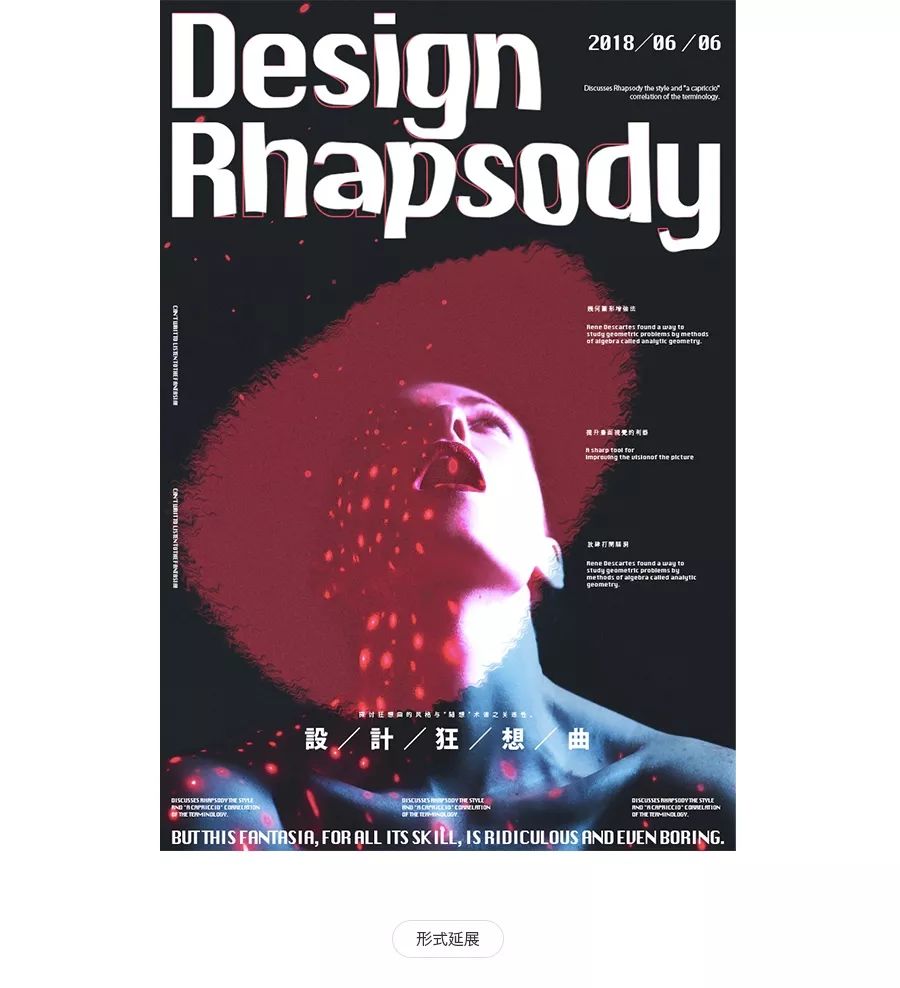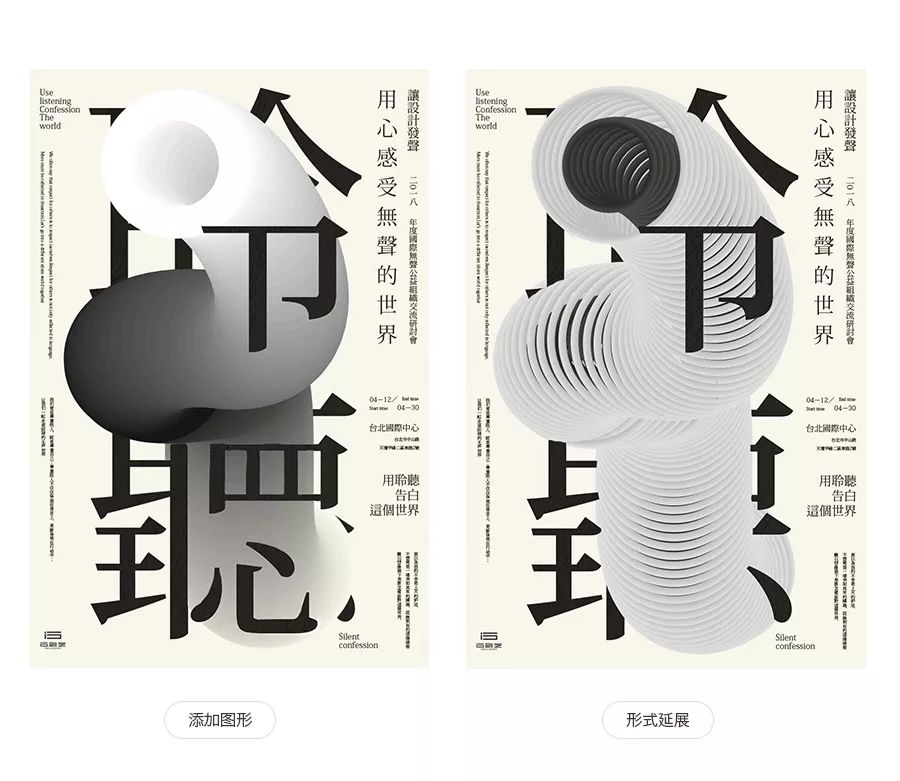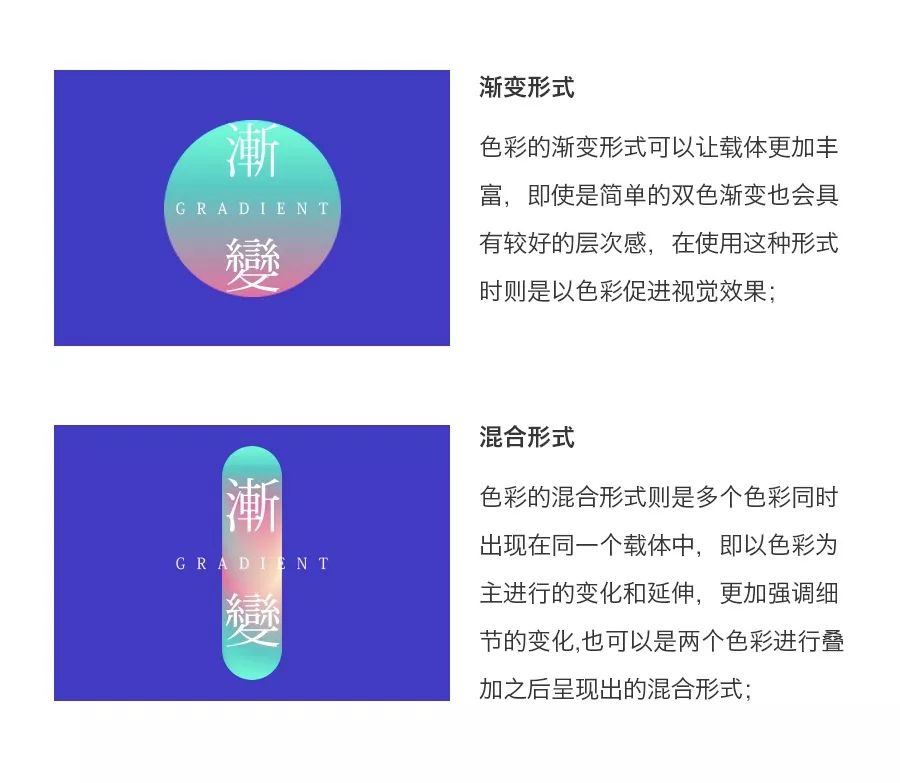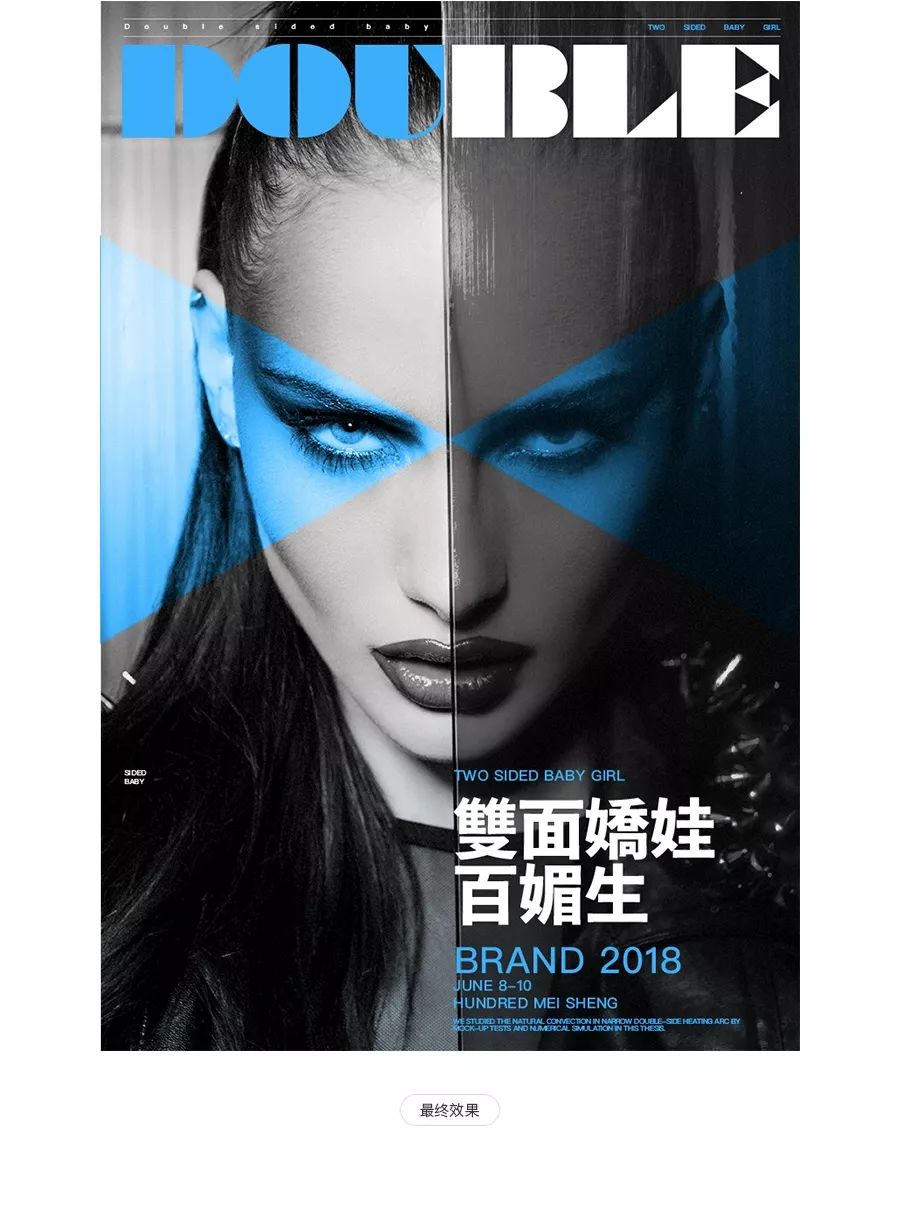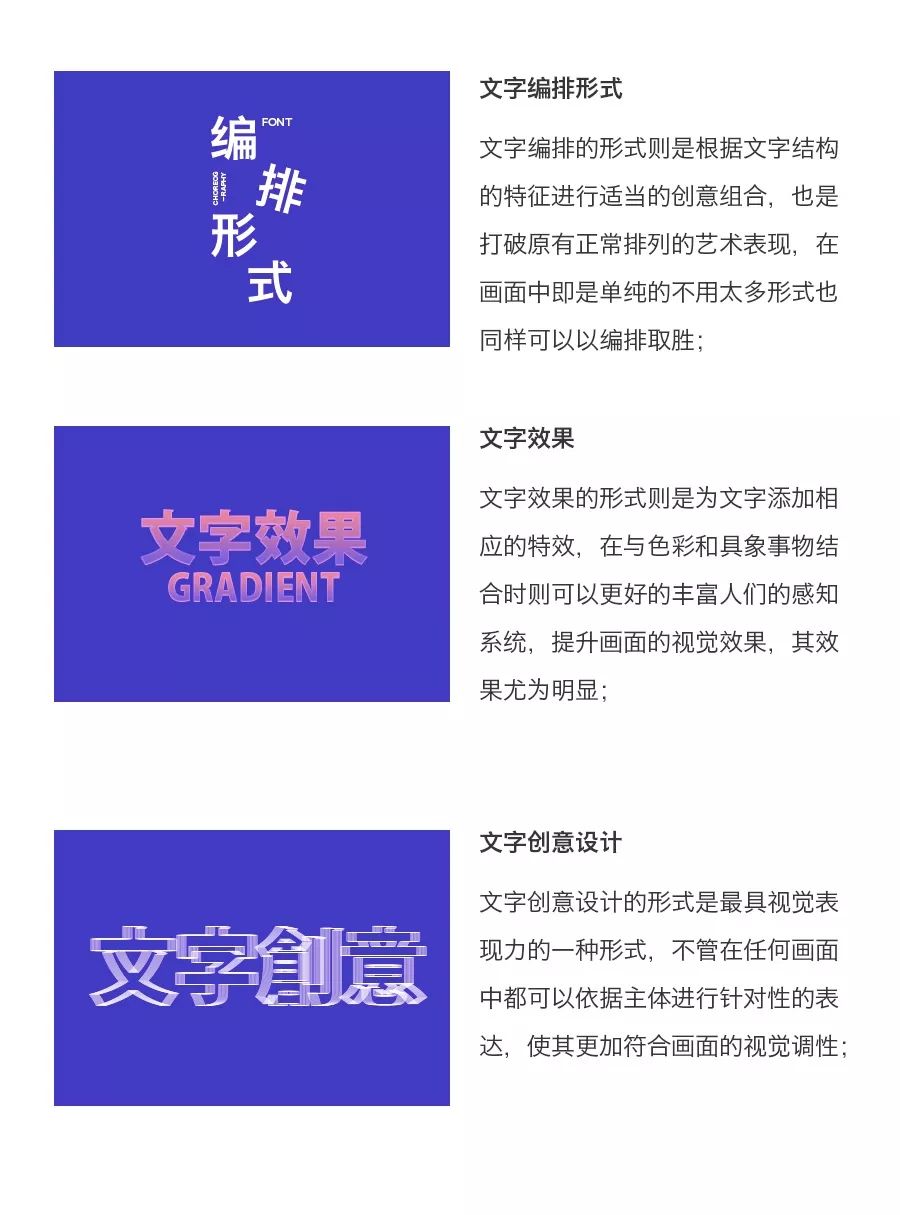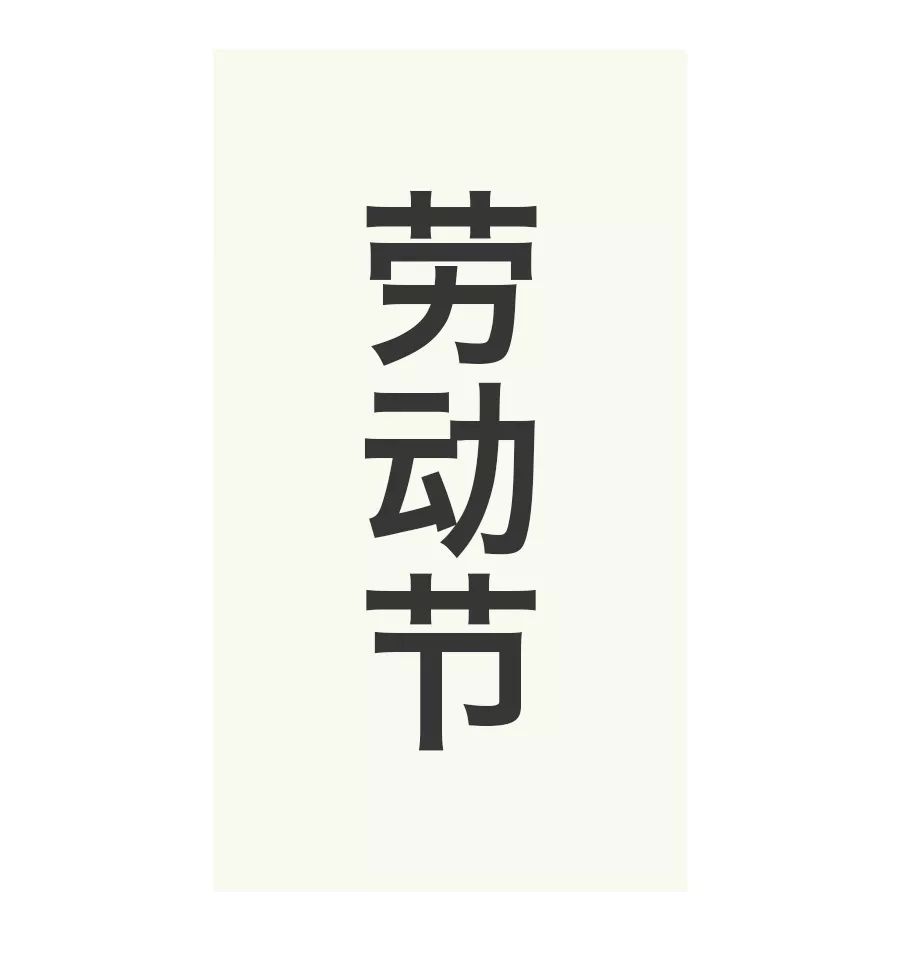
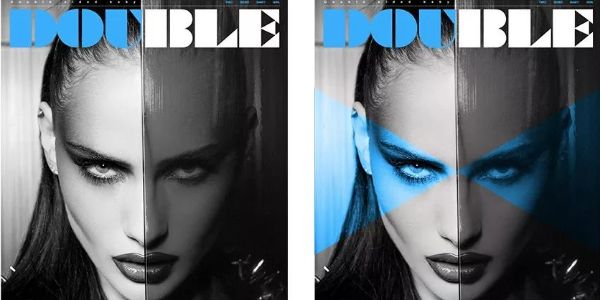
从色彩、文字、版式,提升画面视觉
在设计中表现形式可以说是最难易固定的,同时也是最没有太多规律可以遵循和方法论的,绝大多数情况下我们所看到的画面除了色彩以外其它的基本上都可以称之为形式的表现,即是创意的结合,也是文字和版式有机的统一视觉表现,也是色彩与之融合的载体表现,在视觉设计的四个方向中,表现形式可以作为其它三个方向的创意呈现,也是其它三个方向整合之后所表现出的可视化最直观的感知;
表现形式通俗的来讲就是人眼所看到的感知的呈现,即是把原来的某个主体事物原本的模样在保证能够识别基本特征之外通过符号,表达方式和艺术手段换一种特别的呈现,从而唤醒人们对某个事物特定的认知和视觉感知,以吸引人眼对该事物的兴趣从而促进感知和认知,同时也是改头换面的塑造过程与创意,色彩,编排,文字等等相关艺术手段结合之后的视觉呈现;
图1:
常规形式下的表现只会展现最基础的一些属性,对于视觉的感知并没有太多的影响,而对
于大多数的主体中通常是较为固定的,很难以过多的修饰而去改变主体自身,进而影响人
们人感知,但同时又可以借助于设计中的形式增强主体的表现;
图2:
在常规的基础之上对主体进行形式化的视觉处理,在保证其基本属性的同时为其添加另一
种属性,丰富主体也是为了增强视觉效果,并对版式的编排进行适当的形式处理以两种不
同的形式作为视觉的表现,让画面的视觉效果更加丰富并有冲击力;
基于表现形式的设计上,以色彩和编排的形式可以使画面的视觉效果得到大大的提升,同时让视觉感知更加舒适愉悦;
图1:
常规的表现形式则是尽可能的的展现物体原本的状态和属性,即使添加一些细微的修饰和刻画,在整体的画面表现上并没有太多的视觉突出,色彩也好,版式编排也好对于整体的表现只仅限于常规的形式当中,视觉效果较为平淡,在这种情况下要使得画面视觉效果出彩则可以通过版式的编排和色彩的使用使其达到满意的视觉表现,但同时要保证其基本的可识别性
图2:
当把画面融入创意形式之后,在保证其可识别的基础之上对于感知的表现来说则是换了一种形式,而这种形式则也可以看做是对局部的特殊处理和刻画结果,但就整体的画面而言则与常规的整体表现有所区别,同时使得画面的视觉效果大大提升,更赋予多重想想空间和情感情绪的表现,从视觉感知进而带动心理的变化,从而形成对画面独特视觉记忆符号;
在进行设计构思时,更多的是考虑融入创意之后的表现形式,而色彩版式和信息则是依附于形式的不同进行适当的调整,使其更好的配合形式以表现出完整统一的整体性
表现形式即是可视化的视觉符号,是设计者深度思考依托情感和认知等多方因素,并融合创意手法的思想具体体现,形式与创意密不可分,两者相互依偎,形式是创意的载体,而创意则是形式的表现;在设计中当我们要突出创意时则更多的是想通过巧妙的有机结合而形成一种可视化的,更加直观的表现形式;
图1:
对于主体较为明确的情况下,在进行创意和表现形式的融合时相对来说局限性较大,在常规形势下通常会以文字和编排为创意形式的主要载体进行体现,但同时也是依据主体和整体画面的最终呈现目的为基准进行的演变创意,而很多情况下由于主体较为明确,对于其他画面中所包含的其他内容则会以较为常规的形式去展现,很大程度上则会限制画面的视觉效果;
图2:
针对主体的创意形式融合很大程度上是要进行发散式思维对重点进行提取并融合,在依据主体的基础上对文字和版面编排进行创意融合,同时把主体自身的亮点进行延伸以增强画面的视觉效果,同时与常规形式形成不一样的整体表现形式,但同时又是表达相同的主体和内容,在融入创意的画面中则会让画面更加精致干练,凝集重点;
创意的好坏取决于是否融合的恰当,同时也是形式最直观的视觉呈现,其与风格也是相互关联和转换,可以直接以某种特定的风格形式,也可以吸取其中的特点融合当前的形式中,很多时候创意和形式只是主体内容表现的另一个载体
在进行创意融合时,不管采用何种形式在不改变整体风格的同时使其具有较好的视觉效果,使其主题都能够清晰准确的传达给观者,而针对不同的形式来说版面的编排则需要进行适当的调整以达到整体画面的和谐;当换一种风格时形式也会随之进行变化;
图形作为视觉符号强有力的代表,其自身富有的想象力,变化莫测的形状以及鲜明的形式特征,在设计中赋予极强的形式感,同时在画面也可以发挥出不同的作用以丰富画面增强视觉的表现形式,而自身也由具象型和抽象型等形式表达,并能与任何风格和主体配合创意进行有效的融合,很多情况下也会把原有的主体直接图形轮廓化或者多种图形组合使用,;
图1:
在设计中我们经常会与各种个样的图形打交道,不管是文字或者实质性的产品我们都可以当做是图形,然后对图形进行适当的调整和组合,使其在画面中具有较好的视觉效果,同时又能满足其背后的商业价值,在不加入任何图形,或者不做任何图形轮廓化的处理下,整体的视觉效果则会过于平淡,且不能很好的起到吸睛的目的并与观者引起共鸣,最多也只是信息清楚的摆放;
图2:
而在此基础上可以使用图形的具象化特征,只保留其轮廓并在轮廓上做多种变化和尝试,细小重复的线条在保留主体内容清晰传递时,形成了较为强烈的视觉符号,并使其的表现力和视觉效果大大增强,让整个画面也更加具有冲击力,但切记图形不可过多且复杂而影响整体的识别性,另外在进行多图形组合时则更加需要精简直达表达的中心,以形式突出视觉效果;
而在添加图形的情况下则需要根据主体内容进行适当的图形辅助,图形则更多的是采用抽象化的形式以贴合主体所要表达的内容,并赋予画面更多的想象空间,同时让画面的表现形式更加具有视觉冲击力;
另外,在以图形化为主的画面中,图形除了自身组合形成的形式之外,还会与色彩,材质等等一些图形之外的修饰属性组合成其类型的表现形式以增强视觉效果,不管是抽象或者具像的图形化都可以让其视觉更加丰富;
在画面中通常会出现众多的元素,而其基本的内容则包含色彩,文字,和版面三种元素,同时也是视觉感知的核心所在,而作为表现形式的载体也通常是在这三种类型的元素上所呈现,三者相互关联,此消彼长;
色彩作为平面构成的基础,在设计中是无处不在的,色彩的好坏完全取决于使用的是否合适与合理,同样色彩的形式也是如此,是基于色彩搭配和使用原则上的变化延伸,单就色彩的形式而言,我们通常使用渐变色,混合色三种不同的形式以满足各种不同的需求,同时又需要一定载体赋予其具体的含义,色彩在与载体组合时并没有太多的限制,而是需要注意形式的选择和使用;
先新建一个画布,然后把人物素材植入到画布当中,根据主体的特点和属性调整合适的展示位置,以及做简单的人物色彩对比调整,整体以黑白色调为主;
图1:
整体的版面采用对称式的方式,把文字置入到画面当中进行适当的编排,并保留主体自身的个性特点,在较为固定的主体画面中色彩的形式不易过多且复杂以免对主体造成不好的
视觉效果,而不加有感觉画面缺少了点什么
图2:
根据人物主体和文字信息所要传递出的感觉,然后利用图形的简单色彩混合形式,对人物眼部的位置进行色彩的混合叠加,使其更加帅气与个性,同时在整个人物上面覆盖一个渐变形式的图层,上白下蓝,以更好的修饰视觉
如图案例所示:在主体较为单一且不那么丰富的时候,则可以利用色彩的形式为其增添较好的视觉效果,同时也可以利用色彩的形式对其进行相应的变化延展,以色彩形式取胜;
文字也是设计中不可或缺的一部分,同时也有着非常多的形式可以提供我们使用,而针对于文字的形式则是随着整体的画面和最终的目的而变化的,同时也可以作为独立的存在和使用,其大致可以从三个方面进行形式的变化,即是文字编排,文字特效,文字创意设计进行表现形式的延伸创造,以满足不同需求,丰富画面的视觉感知;
以劳动节为例,尤其是在以文字为主的画面中文字的表现形式则是不可被忽略的重要手段,不管是创意也好亦或者是效果和编排也罢,文字的形式都是画面视觉呈现不可或缺的要素,在新建画布中要考虑到文字的形式表现;
图1:
把主体文字进行创意形式的设计之后置入到画面当中,文字的表现形式则可以根据其字意或者想要表达的意思进行拓展,同时要考虑到最终的视觉呈现效果是否合适具有较好的表现力,以更好的视觉效果展现;
图2:
在此基础上可以对齐进行适当的细节优化,同时也是根据创意形式的表现进行的延展,然后在画面中调整到合适的位置,并把其它描述性的文字置入到画面当中进行编排的形式,另外标题文字则是另一种创意设计形式以提高整体视觉;
版面的形式更多的是所有视觉信息的载体和最终表现手段,在任何版面当中都会有以点线面最基本的构成,而对于这些构成则可以以不同的形式增强其视觉效果,同时版面自身则是以不同的构图和划分形式而影响视觉的整体的表现,对于版面的形式来说更多的则是整体的视觉感知;
首先把我们要表达的主体内容置入到画面当中,针对于不同的主体则可以考虑以不同的版面形式作为表现,当然也可以选择最为具有视觉表现的形式作为基础,这也是根据所要表达的主题而定的;然后对其进行其它的设计;
图1:
在考虑到版面的形式的时候,根据主体的分析和较为合适的展现,从版面的构图形式和划分形式入手把主体内容调整至版面中合适的位置,让其所展现的视觉效果更为妥当与舒适,同时具有一定的艺术表达;
图2:
在处理好版面的形式和主体时,把其它的文字置入到版面中以作为点线面的基本构成信息,并使用网格系统对其进行适当的编排,以贴合其整体的视觉表现,并保证其信息和主体传达的意义较为明确和清晰,使整体更加具有视觉效果;
表现形式虽然变化多样,可创造性也比较强,但在设计时大致可以从文字,版式以及色彩等三个方面进行尝试,即可独立同时也可以混合一起进行使用,在总结的三个表现形式中也是希望可以很好的为大家提供一些努力的方向,在了解形式的时候也能够更好的把控形式的变化以更好的应用到作品当中,更好的满足画面的视觉效果。